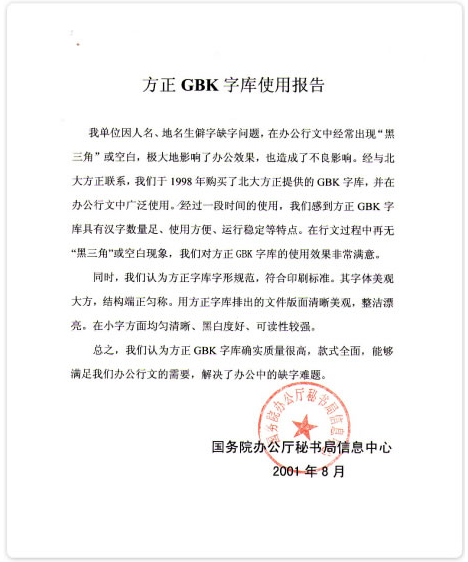
方正字库在国家行政机关公文中的应用
在国标GB/T9704-1999《国家行政机关公文格式》中规定:
·  国家行政机关公文的正文字必须使用仿宋体
·  国家行政机关公文的标题字必须使用小标宋或黑体字
国家行政机关目前使用字库的现状:
·  使用系统中仿宋体和黑体
·  无法使用小标宋体(系统中没有)
·  系统中的仿宋体是GB编码,仅收入汉字6763个,造成在输入人名或地名时经常遇到缺字,方正兰亭办公字库软件可以解决以上问题。
《方正兰亭GBK办公字库》是北大方正电子有限公司开发的标准TrueType中文字库,采用GBK编码,共收录汉字21003字,包含8款GBK字库(黑体、宋体、仿宋、楷体、超粗黑、隶书、小标宋、魏碑)和123款GB编码中文字体(61款简、62款繁),可运行于Windows 95、98、NT、2000和Windows ME等系统中,并能满足在以上系统中运行的办公、排版、视频字幕、雕刻、网页设计、平面设计等字处理软件对中文字库的要求。
也许,在您工作行文的时候,也常常因为人名、地名生僻字遇到下面类似的问题:
·   在个人存款帐户实名制实行以后,就经常碰到凭条上打不出来的“失名户”,名字和身份证不符,给储户办理续存业务带来很大的麻烦。
·   《北京晚报》2000年公布的高考录取名单中,出现了大量的人名“黑三角”;《北京青年报》7月5日第八版也刊登了东城分局东交民巷派出所遇到的棘手问题:计算机字库没有人名生僻字。
同样的问题也出现在户籍管理、辞书出版、古籍整理、地理信息系统中,计算机字库缺字已成为困扰政府、银行、工商、税务、户籍等部门正常办公不可忽视的问题。
为解决办公缺字问题,北大方正针对政府、机关办公行文的特殊需要,开发了针对办公领域的《方正兰亭GBK办公字库》。
这个字库有如下特点:
·  汉字数量足:方正GBK办公字库严格按照国家颁布的GBK编码标准制定,共收录了21003个汉字,完全兼容GB2312-80标准,支持国际标准ISO/IEC10646-1和国家标准GB13000-1中的全部中日韩汉字,并包含了BIG5编码中的所有汉字,能满足政府办公对用字的需求。
·   使用方便:目前中文版的WIN95、WIN98、WINDOWS NT以及WINDOWS 2000都支持GBK编码方案。为方便GBK字库汉字的输入,方正GBK办公字库内带王码98输入法(GBK版),并提供GBK内码字典(用户可查字典找到汉字内码,通过内码输入)。
·   通用性、兼容性强:方正GBK办公字库完全符合国家用字规范和印刷标准,支持多种输出设备和输出方式。
·   字形美观:方正GBK办公字库由字体设计专家设计,字形端庄美观,符合国家颁布的字形规范,并首家通过由国家新闻出版署、国家语言文字工作委员会、全国印刷字体工作委员会联合主持的GBK字库鉴定。同时提供GB编码最新123款方正字库,可以为用户提供丰富的选择。
作为方正GBK字库最早的用户之一,国务院办公厅98年购买和使用了方正GBK字库。由于办公过程遇到无法输入的生僻字而出现“黑三角”或空白现象,影响了办公效果,也造成不良影响。通过使用,国务院办公厅对方正GBK字库的使用效果非常满意,在行文过程中无“黑三角”或空白的现象。新华社已于2000年1月1日起采用GBK编码发新闻稿,《人民日报》及代印点今年6月份全面改用方正GBK字库。北大方正开发的GBK办公字库,对存在缺字问题的行业来说,是一个经济有效的解决方案。方正技术凝聚的这一专业办公字库,将使您的办公更加完美无“瑕”。